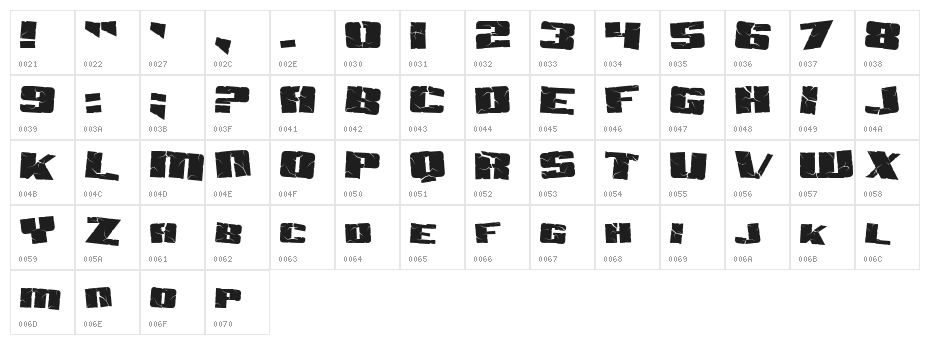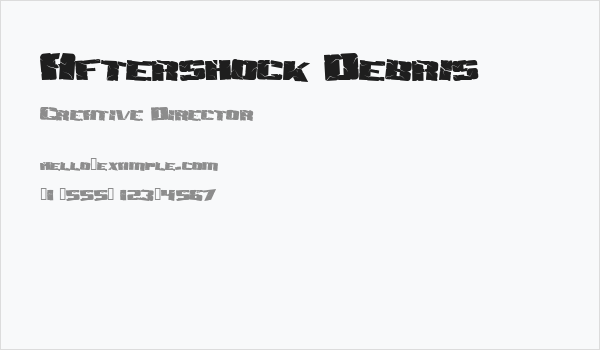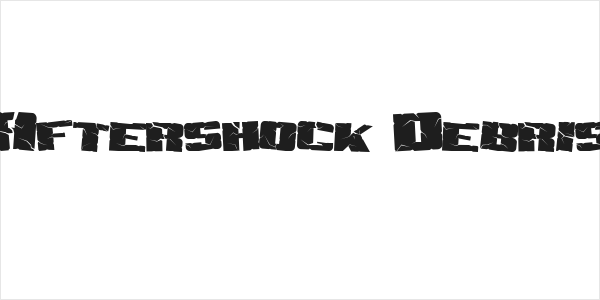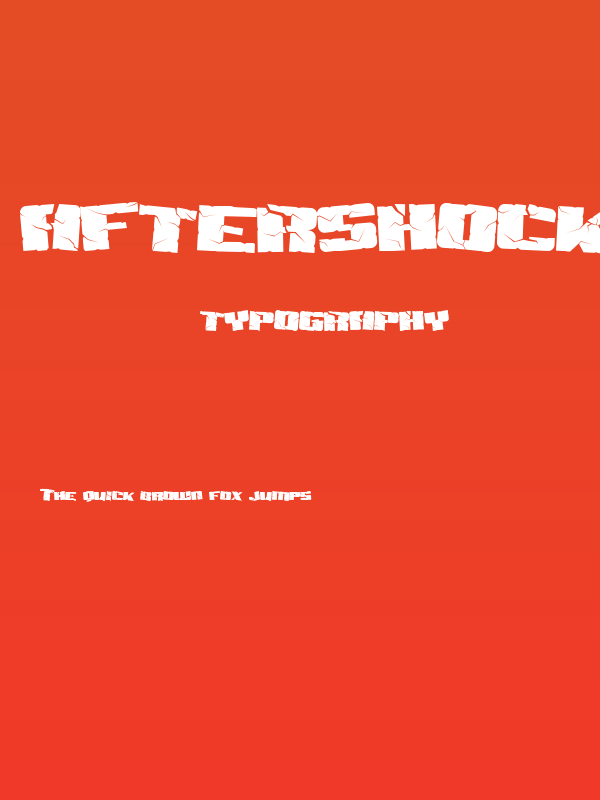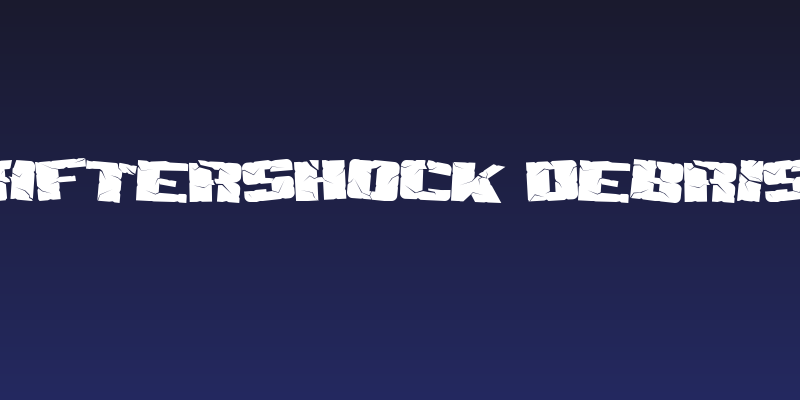
Aftershock Debris Font
| Vorgeschlagene Projekte | Ideal for posters, album covers, video game graphics, and any project requiring a bold, edgy look. |